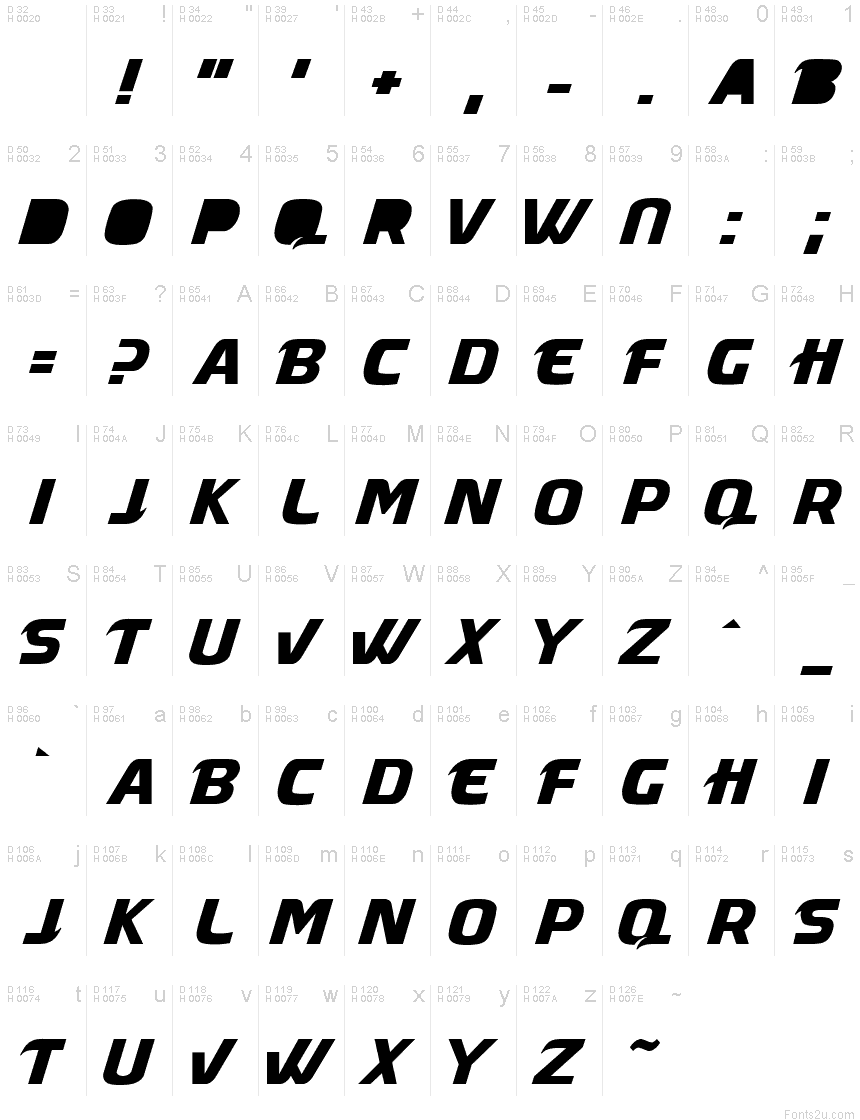
Masque od Apostrophic Labs to nowoczesny, darmowy font typu display. Szerokie, pochylone litery i ostre, diagonalne cięcia nadają całemu krojowi wyścigowy, techniczny charakter. Obłe kształty liter S, Q i U delikatnie łagodzą konstrukcję, podczas gdy kanciaste M i A nadają całości dynamiczny, zwarty rytm.
Masque świetnie sprawdzi się w projektach logo, tytułach plakatów, grafikach sportowych, grach i w brandingu muzycznym – wszędzie tam, gdzie pochylony krój może stworzyć silną linię wizualną. Ten darmowy font doskonale pasuje też do napisów na opakowaniach, wyróżnionych nagłówków i materiałów promocyjnych, ponieważ jego wyraziste formy bronią się same bez żadnych dodatkowych zdobień.